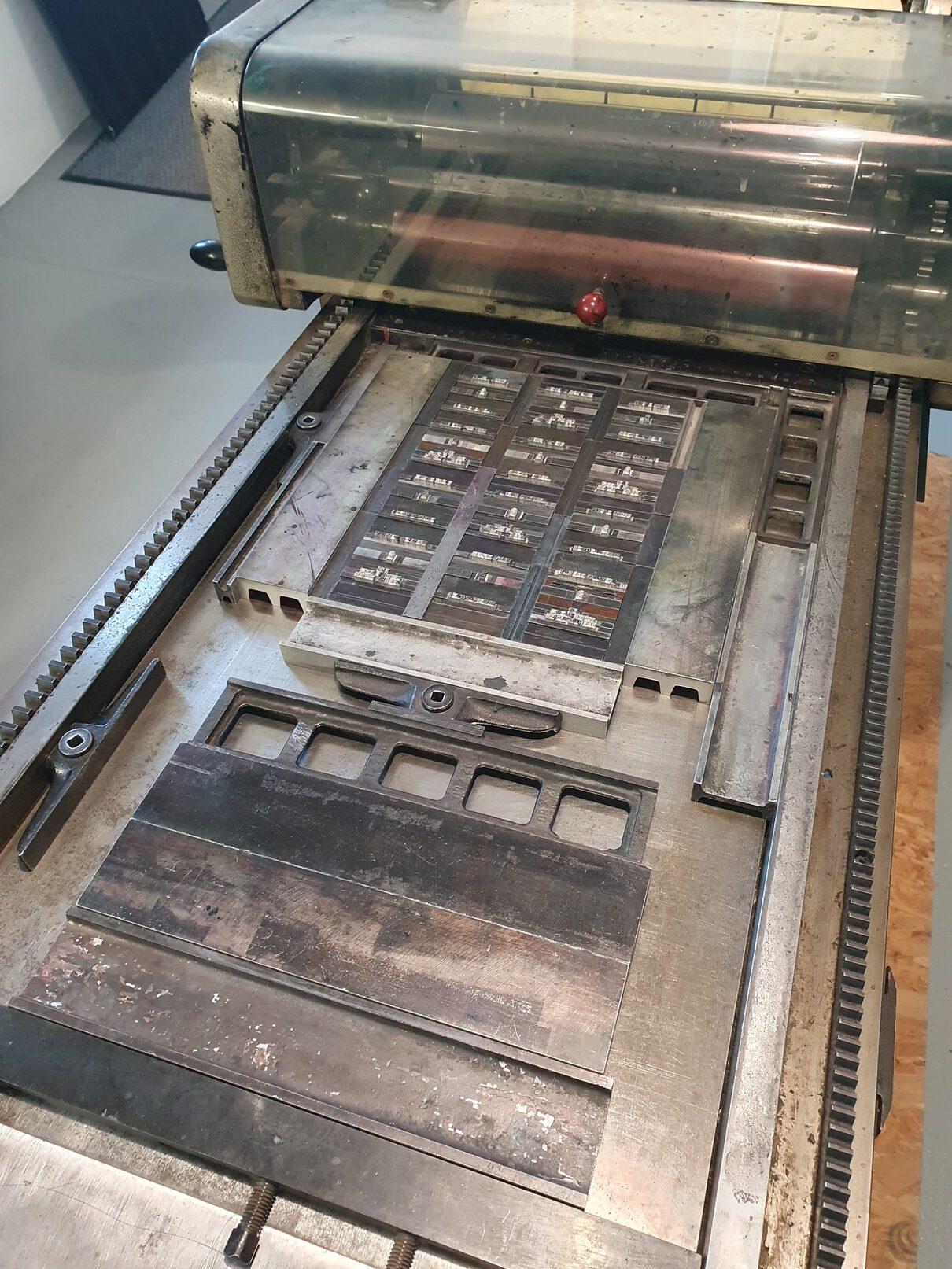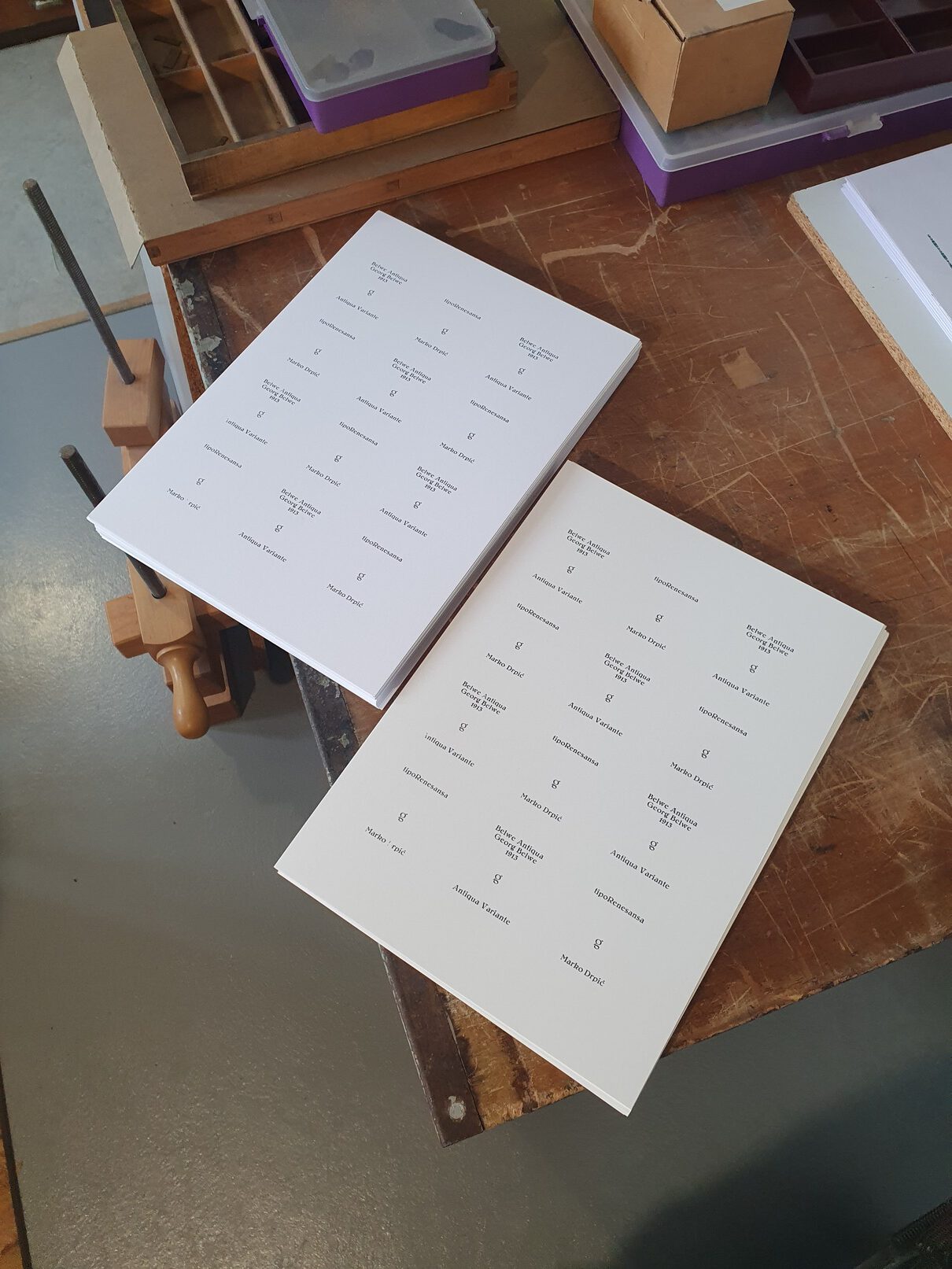
Buchdruck am Oppenweher Moor – Drucken und Kraniche schauen
Meine letzte typografische Reise innerhalb des Walz-Programms des Vereins für die Schwarze Kunst verbrachte ich in der Region des Oppenweher Moors. Diese Kulturlandschaft ist bekannt für die Rastplätze der Kraniche. Um die scheuen Zugvögel zu beobachten, fuhr ich jeden freien Abend an verschiedene Stellen. Pünktlich zur Dämmerung flogen die Kraniche in der typischen Formation zu ihren Schlafplätzen. Nach dem verklingen des tröttenden Gesangs der ebenso ziehenden Gänse, fuhr ich in mein Tinyhaus und zündet schnell ein Feuer im Ofen an. Die ersten Märztage gab es sternenklare und frostige Nächte.
Meine Tage verbrachte ich von 11 bis 19 Uhr in Oppenwehe. In der Buchdruckwerkstatt Fork-and-Broom-Press arbeitete ich weiter an meiner Sammlung von kleinen Buchstaben g. Die in der Dohnaer Buchdruckerei gesetzte Belwe-Antiqua (dazu im nächsten Absatz mehr) druckte ich. Außerdem fand ich interessante Schriften, die ich ebenfalls setzte und druckte. Mein zweites Projekt, einen Lyrikband, konnte ich konzeptuell vorbereiten. Für die von mir angedachte aufwendige Inszenierung des Gedichts fand ich nicht die entsprechenden Bedingungen vor. Die Umsetzung habe ich auf einen späteren Termin, mit anderen Druckpartnern, verschoben.
Die Belwe-Antiqua war mir in Ljubljana als Adrija aufgefallen. Diese Jugendstil-Schrift hat ein sehr eigenwilliges Fähnchen an den Buchstaben V, v, W und w. Was mich besonders faszinierte, war die extrem kurze Schleife des kleinen g. Diese wirkte wie herangezogen um die Unterlängen und vielleicht auch Linienhaltigkeit des Satzes nicht zu beeinflußen. Um genaueres zur Herkunft und zum Designer zu erfahren, recherchierte ich in der Deutschen Nationalbibliothek und in einem Typografieforum. Überraschender Weise fand ich viele Belege zu einer Belwe-Antiqua. Durch die freundliche Unterstützung von Dan Reynolds bestätigte sich diese Zuordnung. Im Archiv des Klingspor-Museums suchte ich mir die Kartei zur Anmeldung der Schriftlizenz heraus. Die Belwe-Atniqua wurde im Jahr 1913 eingetragen, verlegt von der Schriftgießerei J. G. Schelter und Giesecke Schriftgießerei Leipzig. Georg Belwe hatte in seinem späteren Leben eine Professur an der Königliche Kunstakademie und Kunstgewerbeschule Leipzig (heute Hochschule für Grafik- und Buchkunst) inne.
Da ich die Adrija in Ljubljana, in der Werkstatt tipoRenesansa belassen hatte, nahm ich Kontakt mit Marco auf. Durch glückliche Umstände konnte er mir den Kasten, dieser nun zur Belwe-Antiqua gewordenen Schrift, im Verein DruckZeug in Graz übergeben. Zeitgleich erlebte ich mit einer meiner Töchter dort einen wunderbaren Adventsbasar. Wir hatten diesen Termin mit einer Erkundung von Graz verbunden. Die Schrift schickte ich dann nach dem Drucken in Oppenwehe auf selbigen Wege, wieder mit verbundenem Stadtausflug (allerdings ihne mich), zurück nach Ljubljana.
Meine Zeit in der Buchdruckwerkstatt beendete ich vorzeitig, da abzusehen war, dass ich die Arbeiten dort nicht fertigstellen konnte. Offen blieben so die typografische Illustration, der Materialdruck und das Cover. Die letzten Stunden verbrachte ich mit dem Ablegen der genutzten Schriften. Eine Arbeit, die ich aufgrund ihrer Intensität gern ausführe. Das Ablegen trainiert sehr gut für das intuitive Setzen.
Trotz allem war die Zeit in der Werkstatt eine gute Erfahrung für mich. Die Organisation der von mir besuchten Werkstätten, die Arbeitsabläufe und „geheimen“ Tricks bilden eine gute Grundlage für meine aktuelle, eherenamtliche Arbeit im Museum für Druckkunst in Leipzig.